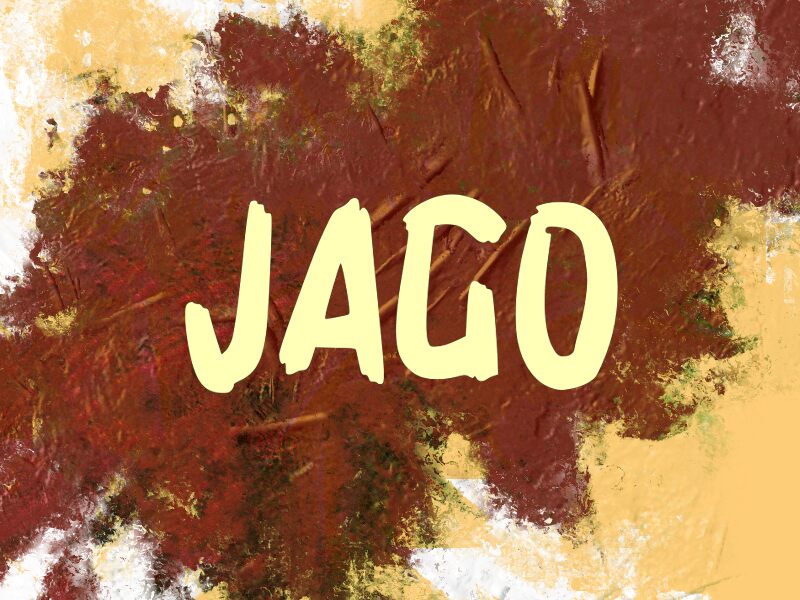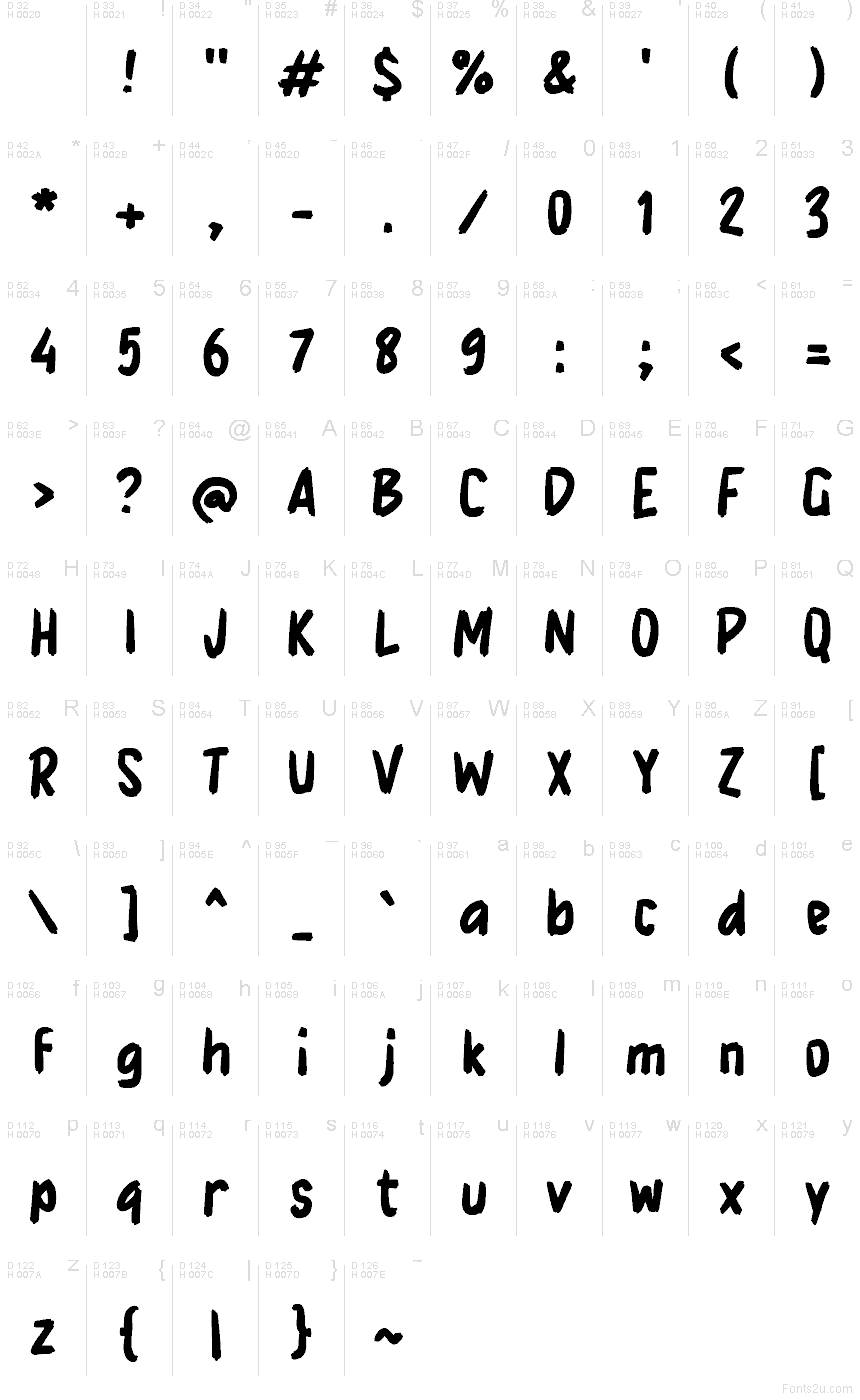
JAGO
Jago di Wep è un font brush gratuito con un'energia grezza e dipinta a mano che trasmette una sensazione rapida e materica. Le lettere sono corpose e irregolari, con bordi smussati, tratti pesanti e una leggera texture a pennello asciutto che mantiene il set dinamico anziché levigato.
Si adatta perfettamente a titoli di poster, grafiche musicali, design streetwear, copertine di zine e titoli dove il testo richiede un impatto visivo diretto e pittorico. Come font gratuito, Jago funziona bene anche per branding sintetico, monogrammi e grandi iniziali, perché i tratti larghi e il ritmo irregolare conferiscono anche a poche lettere una presenza forte e artigianale.